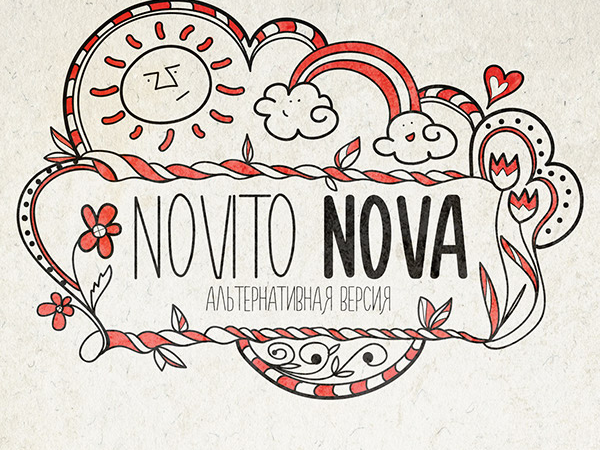
A Novito Nova Font é uma alternativa gratuita à popular fonte Novito, disponibilizada nessa categoria de fontes escritas a mão. Ela oferece duas opções de peso (negro e fino), criadas pelo designer Nina. Esta fonte elegante traz um toque artístico e personalizado para qualquer projeto gráfico. Com sua simplicidade e delicadeza, a Novito Nova é perfeita tanto para subtítulos quanto para nomes de página em sites ou aplicativos. Seja você um amante da escrita manual ou apenas quer adicionar um toque especial à sua próxima criação visual, essa fonte será uma ótima escolha. Ideal para designers que buscam manter a personalidade e o estilo de suas ideias sem comprometer a legibilidade.